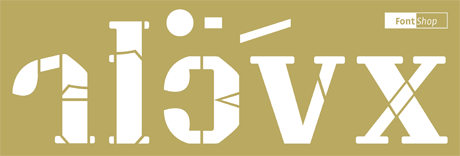
Zum Start der TYPO Berlin 2011 ein Geschenk von FontShop für alle Konferenzbesucher und die Daheimgebliebenen: die Schriftschablone Fontfummler und den kostenlosen Font Fummel im Download. Die Schablone enthält alle wiederkehrenden Formen des lateinischen Alphabets, wozu man sie lediglich mit viel Fantasie drehen und wenden muss. Entworfen wurde das goldene Werkzeug von Lars Krüger (EdenSpiekermann), produziert von Palegra mittels Laserschnitt.
Das Beispielalphabet hat unser Lieblings-Schriftmuster-Künstler Alexander Roth gebaut, auch bekannt durch seine Arbeiten an den FontFont-Release-Heften. Erik Spiekermann über ihn: »Alexander macht die besten Schriftmuster, die ich kenne seit Berthold 1913. Das liegt vor allem daran, dass er die Schriften versteht, die er abbildet.« (vgl. Fontblog-Beitrag Die »besten Schriftproben seit Berthold 1913«). Es steht demnach jedem frei, sofort mit dem Entwerfen der Großbuchstaben für Fummel zu beginnen.